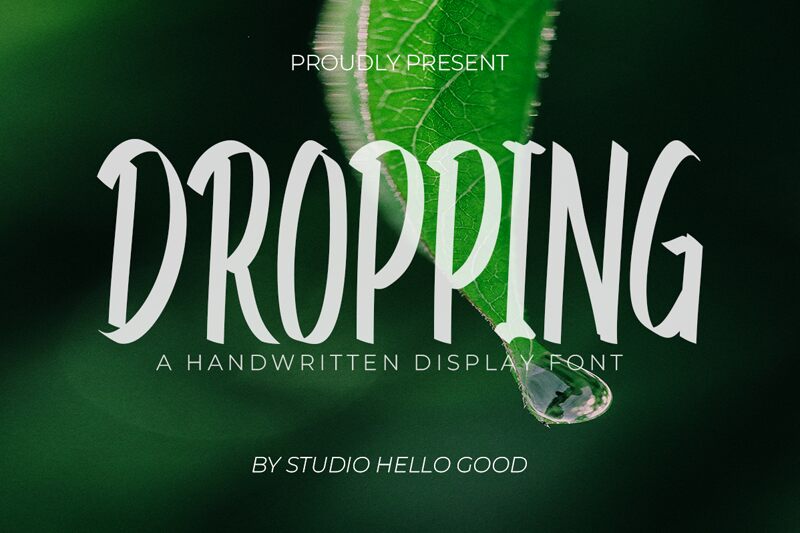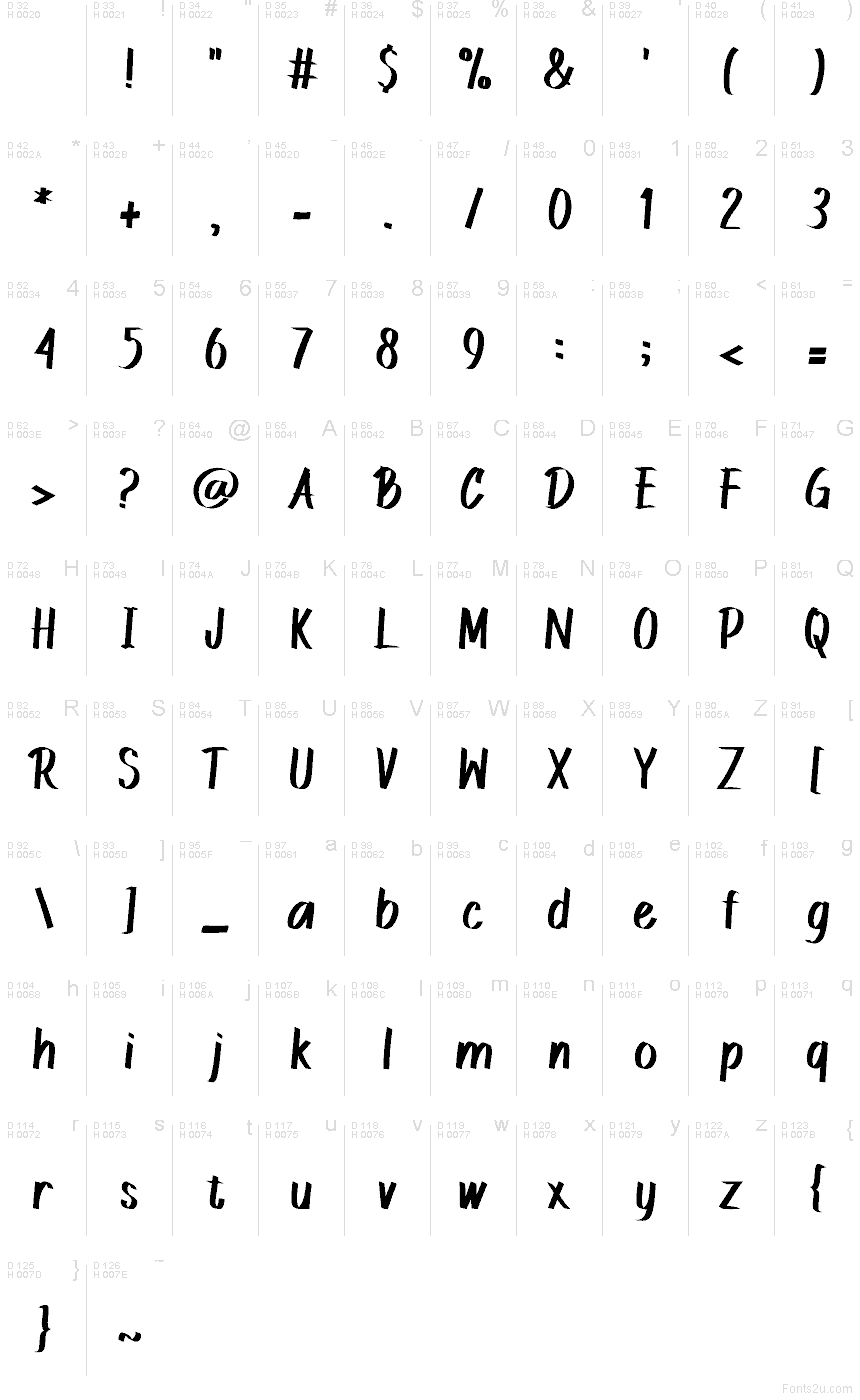
DROPPING Demo
Dropping est une police manuscrite gratuite aux formes hautes et inclinées, caractérisée par des traits effilés et des terminaisons pointues qui lui confèrent une touche calligraphique. La répétition de ses courbes et ses formes étroites et dramatiques confèrent à cette police un aspect éditorial affirmé, bien loin d'une simple écriture manuscrite décontractée.
Dropping est parfaite pour la création de logos, les titres d'affiches, les pochettes d'albums, le lettrage de tatouage et les graphiques de citations courtes où son rythme anguleux peut porter toute la composition. Cette police gratuite fonctionne également très bien pour les accents sur des invitations ou le marquage d'emballages, car ses formes sculptées à la main apportent une signature forte à de courts textes.